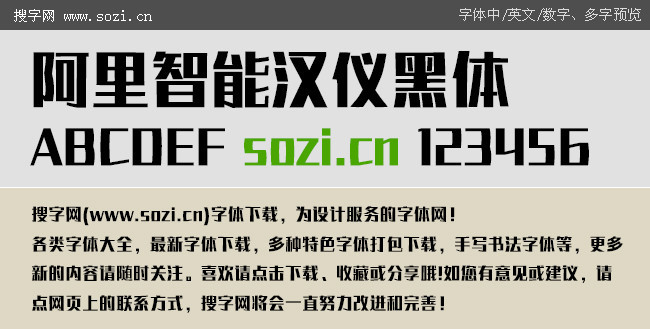
阿里智能漢儀黑體
搜字網(wǎng)提供一款阿里智能漢儀黑體字體下載,阿里智能漢儀黑體是一款漂亮的藝術(shù)黑體字體,是漢儀字庫聯(lián)手阿里巴巴打造的第一款A(yù)I字體產(chǎn)品,漢智能黑體基于黑體的橫豎基本特征,加大橫豎粗細(xì)比例,字面飽滿填充整個(gè)內(nèi)框,讓字體更加醒目,視覺沖擊力極強(qiáng),能夠很好的與用戶對(duì)話,非常適用于電商類廣告設(shè)計(jì)! 阿里漢儀智能黑體將免費(fèi)提供給阿里用戶在阿里平臺(tái)進(jìn)行使用!】